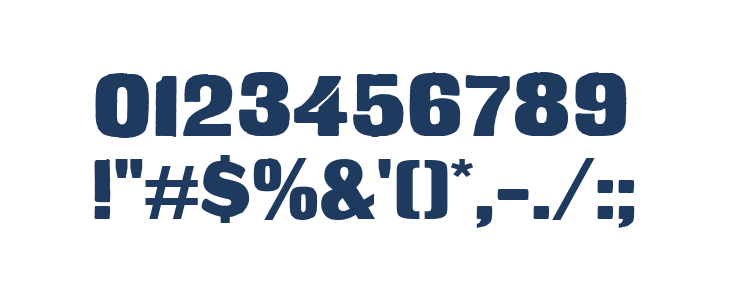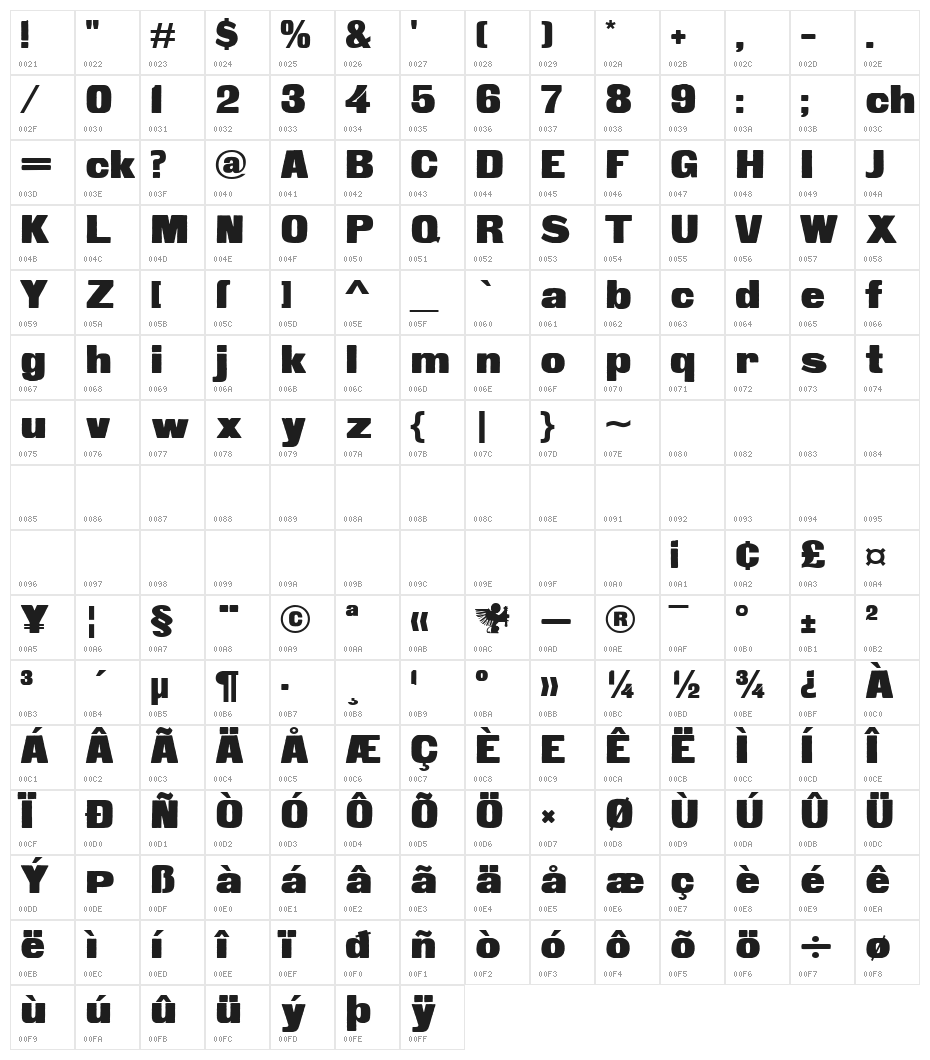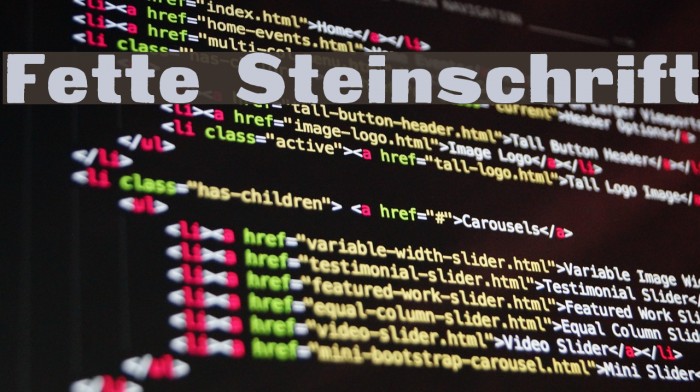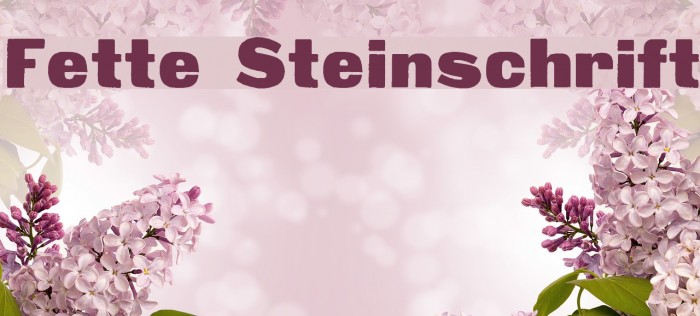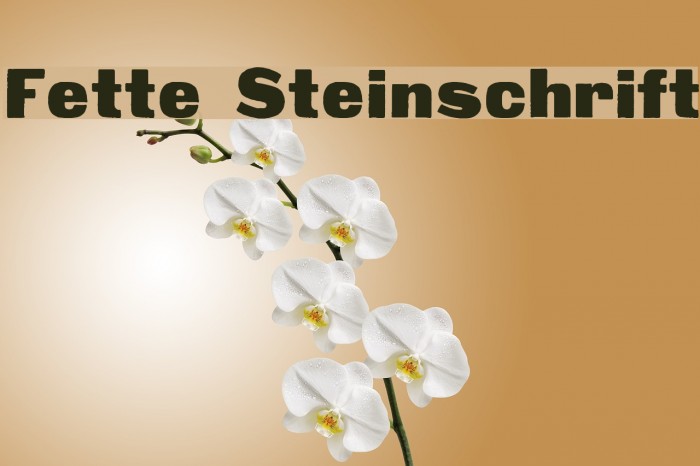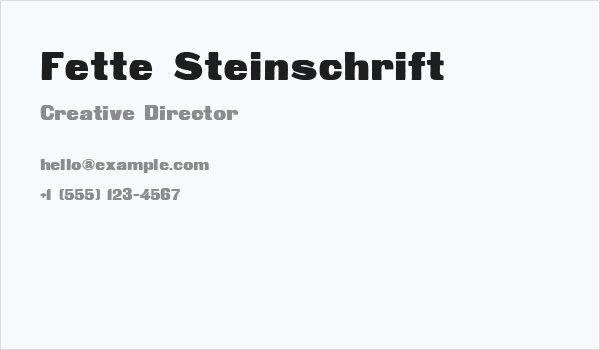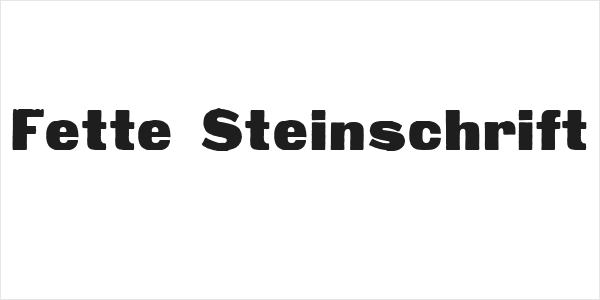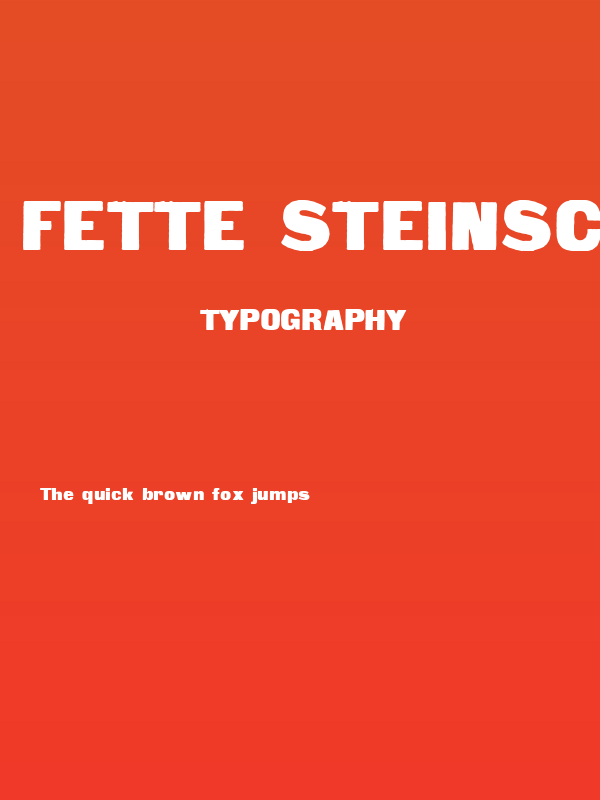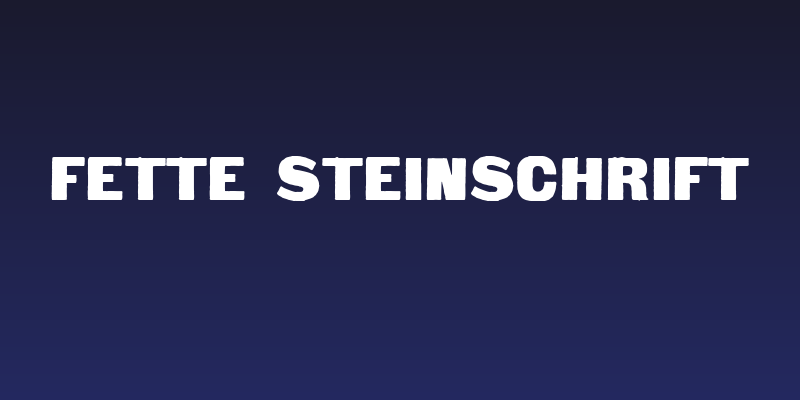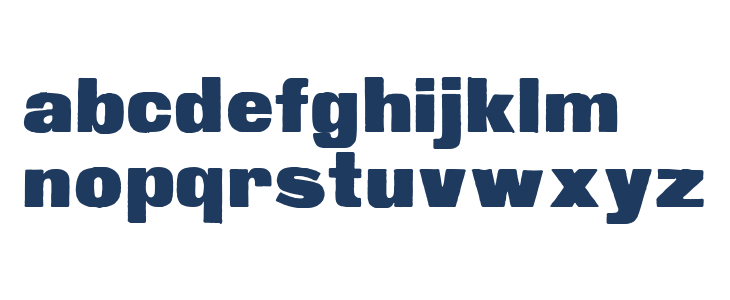
Fette Steinschrift Font
✎ Distorted Eroded
| Gesamtstil | Classic |
| Vorgeschlagene Projekte | Ideal for posters, headlines, logos, and branding materials that require a bold statement. |